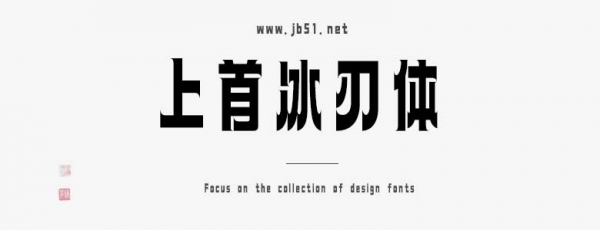
上首冰刃體是由上首造字字庫(kù)出品的字體,這款字體筆觸略顯粗實(shí),筆畫(huà)疏密有致、規(guī)整雅致、剛?cè)嶙厩桑m合應(yīng)用于藝術(shù)設(shè)計(jì)、平面宣傳設(shè)計(jì)、網(wǎng)頁(yè)設(shè)計(jì),書(shū)法字帖等領(lǐng)域,需要的朋友可以前來(lái)本站下載。
上首冰刃體,簡(jiǎn)體中文約6763字,這款字體風(fēng)格刺激、現(xiàn)代。其筆畫(huà)疏密有致、規(guī)整雅致、剛?cè)嶙厩?,彰顯個(gè)性與獨(dú)特。適用于搭配標(biāo)志、廣告標(biāo)語(yǔ)、商業(yè)廣告等高端屬性。